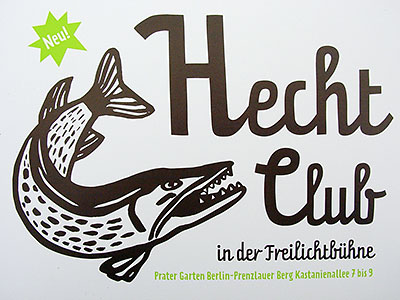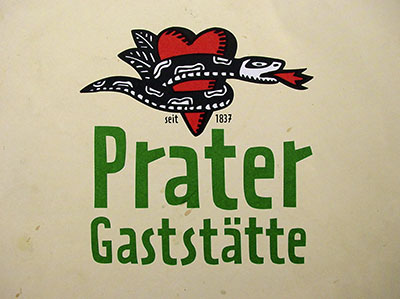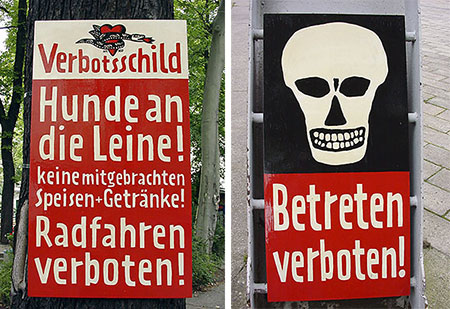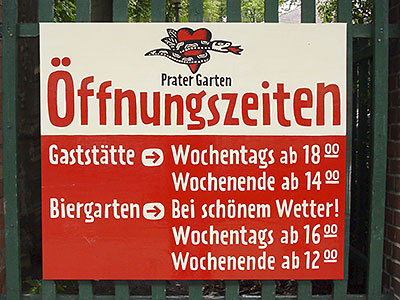
Prater: eine Schrift wie handgemaltAls nach dem Mauerfall Berlins ältester Biergarten wieder
öffnete, übernahm ein junger Designer die visuelle Ausstattung. Wie
man Parolen auf hohem Niveau pinselt, lernte er schon in der Schule. Gepaart mit
dem akademischen Geist der Kunsthochschule servierte er dem Restaurant eine
![]() Es gibt nur wenige Kunstschulen, denen man einen eigenen Stil nachsagen
kann. Die Kunsthochschule Berlin (KHB) in
Weißensee gehört dazu. Auf den Gebieten Illustration und Grafikdesign
pflegen ihre Absolventen eine klassische, unverwechselbare Handschrift. So auch
der junge Henning Wagenbreth, der 1987 sein Diplom an der KHB ablegte.
Als kurz nach dem Mauerfall der Prater, Berlins ältester Biergarten, wieder öffnete, kümmerte sich Wagenbreth um die visuelle Ausstattung des zuletzt als Kreiskulturhaus genutzten Areals. Wie man Parolen und Wandzeitungen auf hohem Niveau pinselt, lernte man in der DDR bereits in der Schule. Gepaart mit akademischem Wissen bescherte Wagenbreth dem rustikalen Restaurant im Prenzlauer Berg eine Beschilderung, die weltberühmt wurde, denn der Prater reifte in den Berlin-Führern rasch zum Geheimtipp. ![]() Das gemalte Eingangsschild des Prater-Biergartens im Prenzlauer Berg, aufgenommen im September 2000 ![]() Alles handgemalt: die Prater-Öffnungszeiten vom September 2000 ![]() Selbst strenge Verbotsschilder wirken mit der Prater-Schrift sympathisch (September 2000) Die Hauptrolle auf den Prater-Schildern spielte eine weiße, holzschnittartige Schrift. Ende der 90er Jahre begegneten sich der »eBoy« Steffen Sauerteig und Henning Wagenbreth, um über eine Digitalisierung der Schrift nachzudenken. Sauerteigs FF Typestar war zu dieser Zeit bereits ein Bestseller. Die Fonts der Prater-Familie sollten, trotz Digitalisierung, ihren handgezeichneten Charakter behalten, also die unregelmäßigen Strichstärken, die wechselnden Strichrichtungen und die stolpernden Buchstabenabstände. Weil das lebendige Schriftbild seine Glaubwürdigkeit verliert, wenn zwei identische Buchstaben mit genau denselben Unregelmäßigkeiten nebeneinander stehen, wurde zu jedem Erstfont (gekennzeichnet mit dem Namenzusatz »One«), ein Zweitfont »Two« gestaltet, dessen Unregelmäßigkeiten von denen des Erstfonts abwichen. Viel Arbeit, aber im Ergebnis sehr überzeugend. Im Sommer 2000 erblickte die digitalisierte FF Prater (FontFont) das Licht der Computerwelt. ![]() Identische Doppelbuchstaben der FF Prater One ![]() Identische Doppelbuchstaben der FF Prater Two ![]() Erst die Kombination (Flash-Demo auf Wagenbreth-Seite) aus Prater One und Two bringt den authentischen Handschriftcharakter Für die Benutzer der Schriftfamilie bedeutet dies, dass sie munter zwischen Prater One und Two wechseln sollen und dürfen. So erhält jede Prater-Zeile einen wahrhaft handgezeichneten Charakter. Beim Setzen größerer Texte ist die Verwendung beider Fonts Pflicht. Da unser Auge die Unregelmässigkeiten der Schrift in kleineren Graden jedoch kaum wahrnimmt, brauchen hier die Fonts nicht gewechselt werden. Kurz nach Erscheinen der Prater-Grundschriften (Sans und Serif) bekam die Familie bereits Nachwuchs: die Schreibschrift FF Prater Script inklusive Varianten kam hinzu sowie die 3D-Display-Schrift FF Prater Block, die sich sogar zweifarbig aufbauen lässt. Damit wuchs die temperamentvolle Familie zu einem Komplettsystem heran, das durch die Serifen-Version auch in kurzen Texten ausgezeichnete Sympathiewerte bringt. ![]() Neue Veranstaltung im Jahr 2000, neue Prater-Schreibschrift (digitalisiert) ![]() Die aktuelle Visitenkarte der Berliner Prater Garten GmbH, natürlich gestaltet und gedruckt mit der FF Prater Herausgegeben: Mi - August 24, 2005 at 12:54 nachm. | |